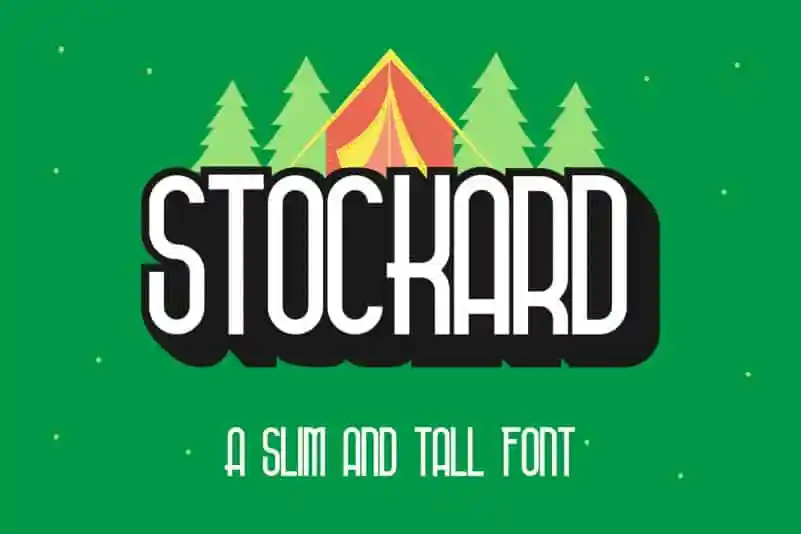
Stockard Sans Serif Font – Download Grátis
A Stockard Sans Serif é uma elegante e versátil fonte sem serifa para uso casual ou criativo. Com seu design alto e compacto, ela se adequa perfeitamente a qualquer situação onde você deseja transmitir simplicidade, descontração e modernidade. Suas linhas levemente curvadas dão ao texto um toque de personalidade, tornando-a ainda mais agradável para ler em grandes tamanhos ou para uso em ambientes digitais. Seu estilo fun e versátil a torna uma escolha inteligente para designers de marca que buscam criar mensagens modernas e eficazes. Ideal tanto para aplicações online quanto offline, a Stockard Sans Serif é uma ótima opção para quem valoriza estética e funcionalidade no design gráfico.